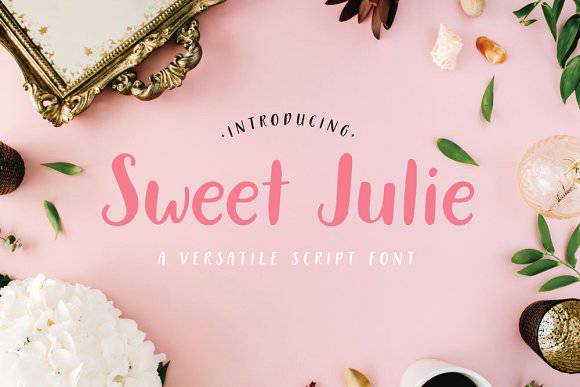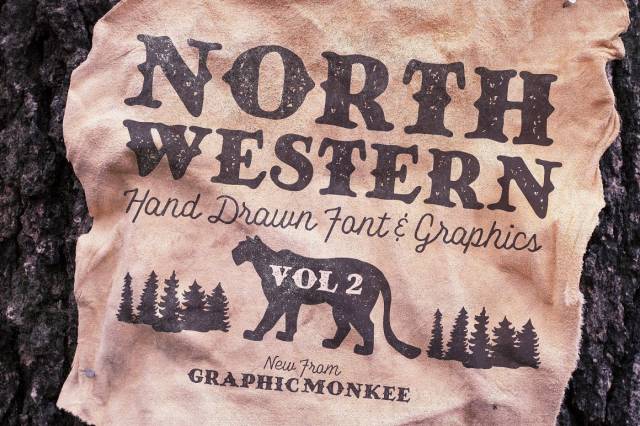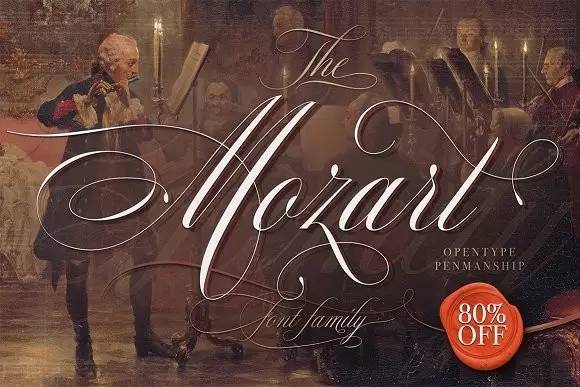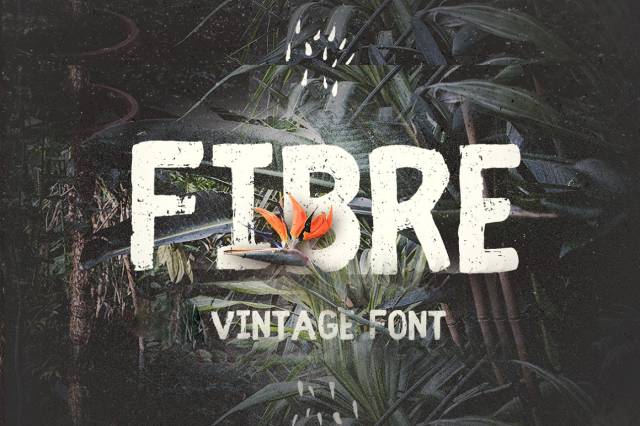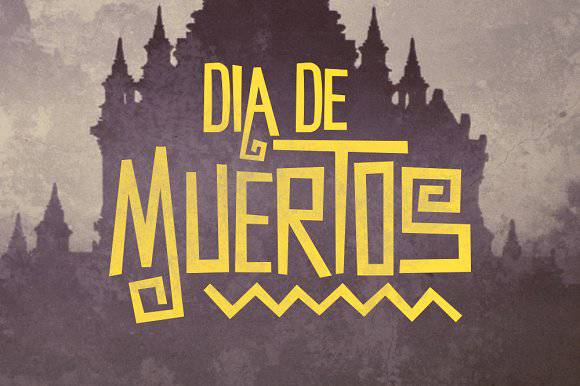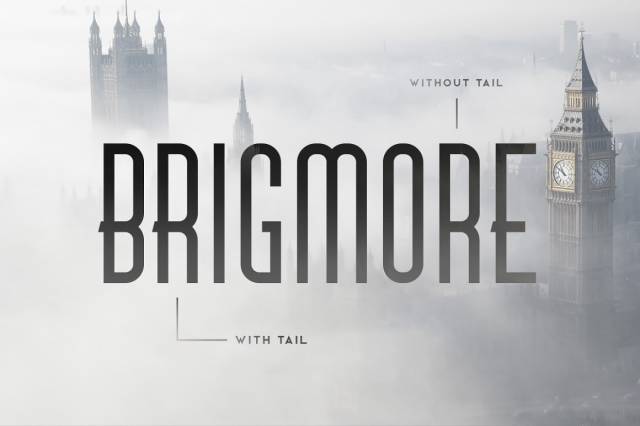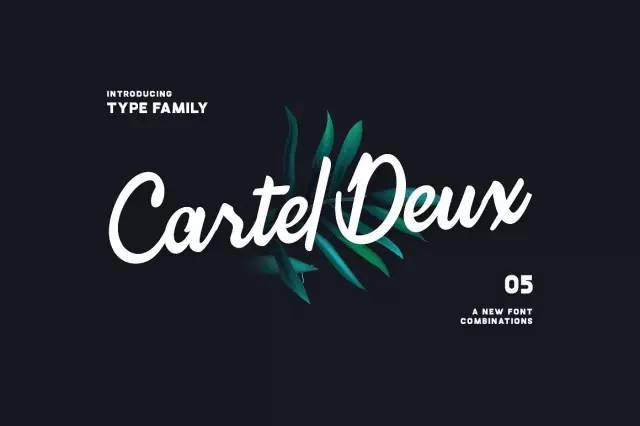
字体的外观带来的影响到底有多大?
让我们从四个方面来分析字体对设计的影响,暗示,视觉与语意,清晰度以及外观,分析这四点是如何在设计或者运营当中起的重要作用。
大家知道色彩心理在展示设计或是品牌的时候起了很大的作用,产品抉择有百分之九十是依靠色彩进行的,虽然某些颜色在特定文化环境当中具有特定意思,但是研究表明适当运用色彩是有助于扩大品牌的识别度的,可见心理学在设计中的重要性,然而关于心理学对字体设计的研究却少之又少。
字体的第一层作用如何通过文本来表达意思,第二层作用大部分研究都集中于探究字体选择对受众的影响。字体的选择对于整个设计或者品牌推广来说有着很大的影响,人们会通过字体去推断当中的意义。此外,在一个以文字为主的包容性设计里面,字体的选择是否清晰明了会影响到整个设计给人的印象。
以下让我们从四个方面来分析字体对设计的影响,暗示,视觉与语意,清晰度以及外观,分析这四点是如何在设计或者运营当中起的重要作用。
暗示
受众一般都会下意识地通过字体的风格来对一个设计做出一些推断,例如,如果使用粗体或是一段文本加粗了,会让人觉得它们比较重要,因为它们从整个设计中凸显来出来。其次,斜体的文本也是会让人觉得是重点,有时候也会表示一种讽刺的意思,所以多留意一下在阅读的时候出现了的加粗和斜体词语吧。
象征主义风格的设计非常常见,但是使用的时候要谨慎注意。手写的字体经常会运用其中,因为它会让人觉得优雅且蕴含底蕴,所以很多奢侈品牌或是婚礼请柬上面都会出现手写字体。
The Mozart Script By Blessed Print in Fonts
另外,为了更加准确表达特定的主题,往往会专门重新设计字体。像是以下的例子一样,这款名为he North Western的字体就是一款复古的,令人感到有户外气息的字体。
North Western Font + Vectors Vol 2 By Trailhead Design Co. in Fonts
复古字体的影响,即使受众并没有仔细阅读文本内容,做旧复古的手写字体都会勾起他们的感觉,使他们觉得这是一条特别的信息。
Fibre - Vintage Font By Wild Ones in Fonts
设计师或者品牌推广通过用特定的字体,可以自然而然引导大众去推断设计的目的和体验感。这就需要我们除了考虑什么样风格的字体会有什么样的心理暗示,还需要想象同系列的字体会不会有不同的效果。
视觉和语意
字体的外观还能给让人“留下印象”的作用,尤其是当字体的外观和语意切合的时候,这不仅仅特指上文提到的为了宣传主题而设计的字体,还包括在文本里面的基础字体,字体粗细或者高度变化都会改变人的印象。根据格式塔理论举的例子,“高”这个字如果是用细长的字型表示,会很直观的让人有有画面联想,效果比同系列常规宽度的字型要好很多。其实在1986年开始,就有研究提出,字体的选择正确与否会影响到产品推广效果。
Brigmore Typeface By Tugcu Design Co. in Fonts
视觉和语意之间的联系多半是自然想到的,而字体元素之间蕴含的心理学往往不会特别明显。在2015年的时候,有人为了探讨字体设计中是否有心理学原理而做了实验。实验里,人们将一些味觉的词语——甜,酸,咸,苦,用特定的字体写出来。
实验者用比较圆润的字体来写“甜”,而“酸”、“咸”、“苦”这些味道则是用棱角分明的字体写。
Sweet Julie Font By Birdesign in Fonts
通过这个实验,人们发现圆润流畅的字型会更让人觉得亲近,讨喜,并且更加容易阅读。相反,棱角分明的字体就不那么会让人有亲切感。
Cartel Deux • 5 Styles • 75% Off By TyfoMono™ in Fonts
清晰度
在版式设计当中,清晰度比文本的可读性还要重要。很多关于字体心理学的研究都觉得“字型越清晰文本越容易阅读”,其实并不是这样,字体读起来实际上更需要花时间,不过反过来说,正因为这种“不清晰”使得字体在版式当中更能让人记住。
外观
有研究表明,独特新颖的字体设计同样会影响阅读速度。这种个性鲜明的字体很自然会吸引到观众的注意,因此也自然而然会有更好的回响。不仅仅字体风格与它描述的词之间的一致性会影响设计的意思,视觉和语意之间的分离也会导致读者需要花费更多时间去理解设计内容。
Muertos Typeface By Tugcu Design Co. in Fonts
然而,并不能单单靠用复杂的版式设计来增加人们的记忆里,虽然新颖独特的设计能够提高注意力,加深印象和提高推广率,但是过度复杂的字体会使观众无法将文字和设计联系起来。如果使用或者选择字体的时候稍有不慎,除了会使字体和设计中的元素之间的意义就会分崩离析,还会导致受众觉得这不是一个好的设计。
结论
用设计传达信息的时候,字体选择的重要性一点都不亚于色彩选择。心理学研究表明,在版式设计中选择字体的时候应当注意上述的四点:暗示,视觉与语意,清晰度和外观,使得整个设计是行之有效的。